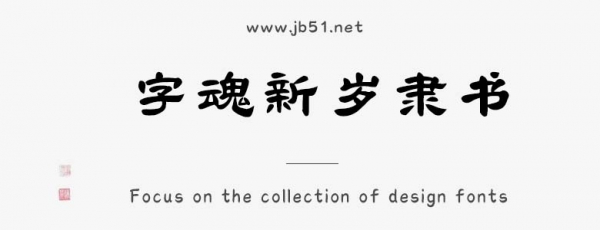
字魂新歲隸書是由字魂字庫推出的楷體字體,包含9503個中文、字母、 符號和數(shù)字,具有中國風(fēng)的風(fēng)格,可以滿足您設(shè)計(jì)上的各種需求,適合應(yīng)用于藝術(shù)設(shè)計(jì)、平面宣傳設(shè)計(jì)、網(wǎng)頁設(shè)計(jì),書法字帖等領(lǐng)域。
字魂新歲隸書字體是一款商用的隸書字體,該字體包含9503個中文、字母、 符號和數(shù)字,具有中國風(fēng)的風(fēng)格,可以滿足您設(shè)計(jì)上的各種需求,該字體主要用于標(biāo)題等場景, 您不但可以在字魂網(wǎng)下載字魂新歲隸書字體,同時還有眾多毛筆書法字體、創(chuàng)意字體等可供選擇!